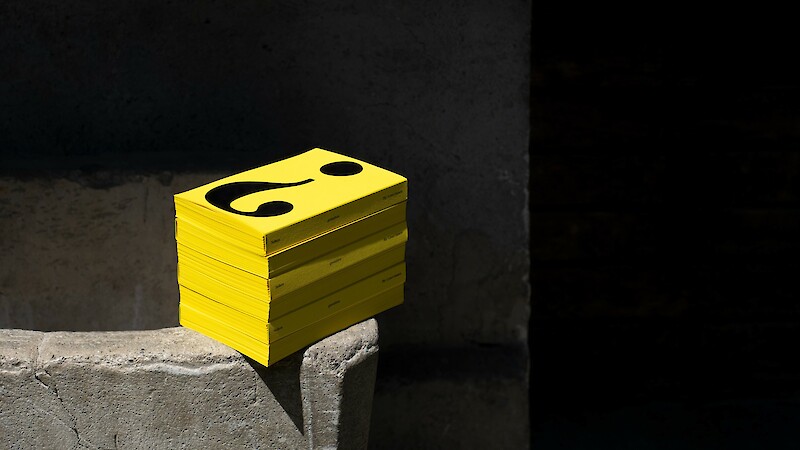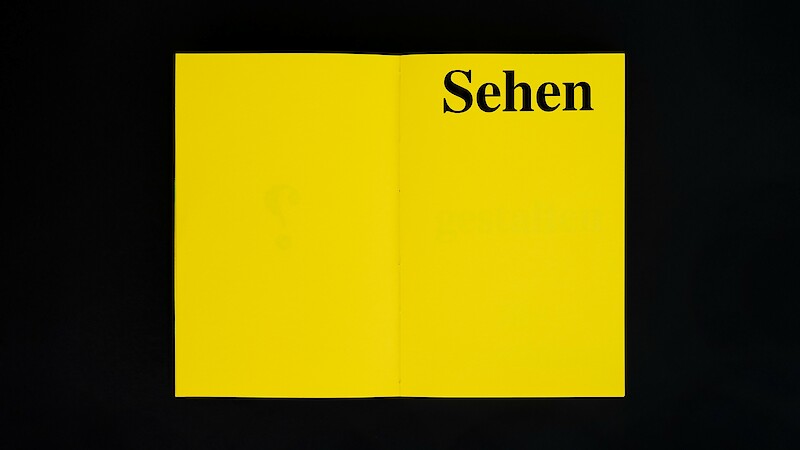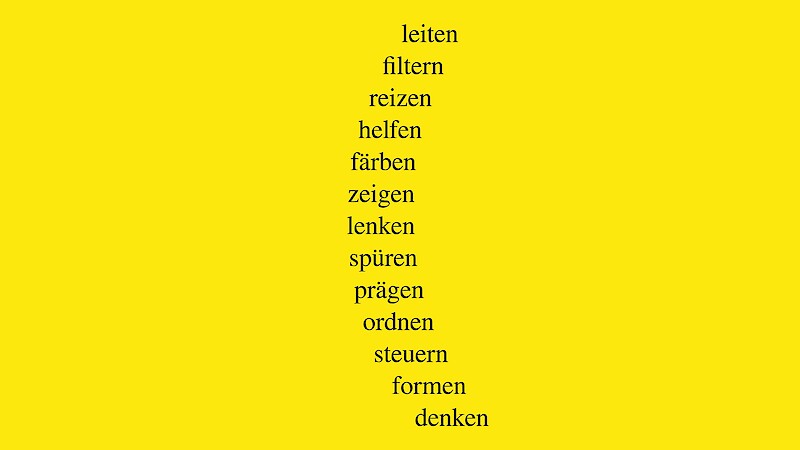
Typografie in Büchern ist ein Dialogwerkzeug. Sie verbindet Menschen, indem sie Wissen vermittelt. Lesen und Lernen sind jedoch herausfordernd, Inhalte müssen folglich nicht nur physisch verfügbar, sondern auch intellektuell zugänglich sein. Wie ist die heutige Erscheinungsform der Typografie entstanden? Welche Aspekte beeinflussen die Wahrnehmung von Typografie? Und wie kann insbesondere Makrotypografie diese Vermittlung in Fach- und Sachbüchern unterstützen? Um Antworten zu erhalten, wurden Lese-, Lern- und Gestaltungsmuster im Zusammenhang mit Büchern beobachtet, gesammelt und reflektiert. Durch die Verknüpfung solcher Muster gibt die Arbeit Anstösse für eine Typografie in Büchern, die Leser:innen, Semantik und Zeitgeist in den Vordergrund stell.
Typography in books is a dialog tool. It connects people by conveying knowledge. However, reading and learning are challenging; consequently, content must not only be physically available, but also intellectually accessible. How did the current form of typography come about? What aspects influence the perception of typography? And how can macrotypography in particular support this communication in technical and nonfiction books? To get answers, reading, learning, and design patterns in books were examined, collected, and reflected upon. By linking them, the work provides impulses for a typography in books that serves readers, semantics, and zeitgeist.